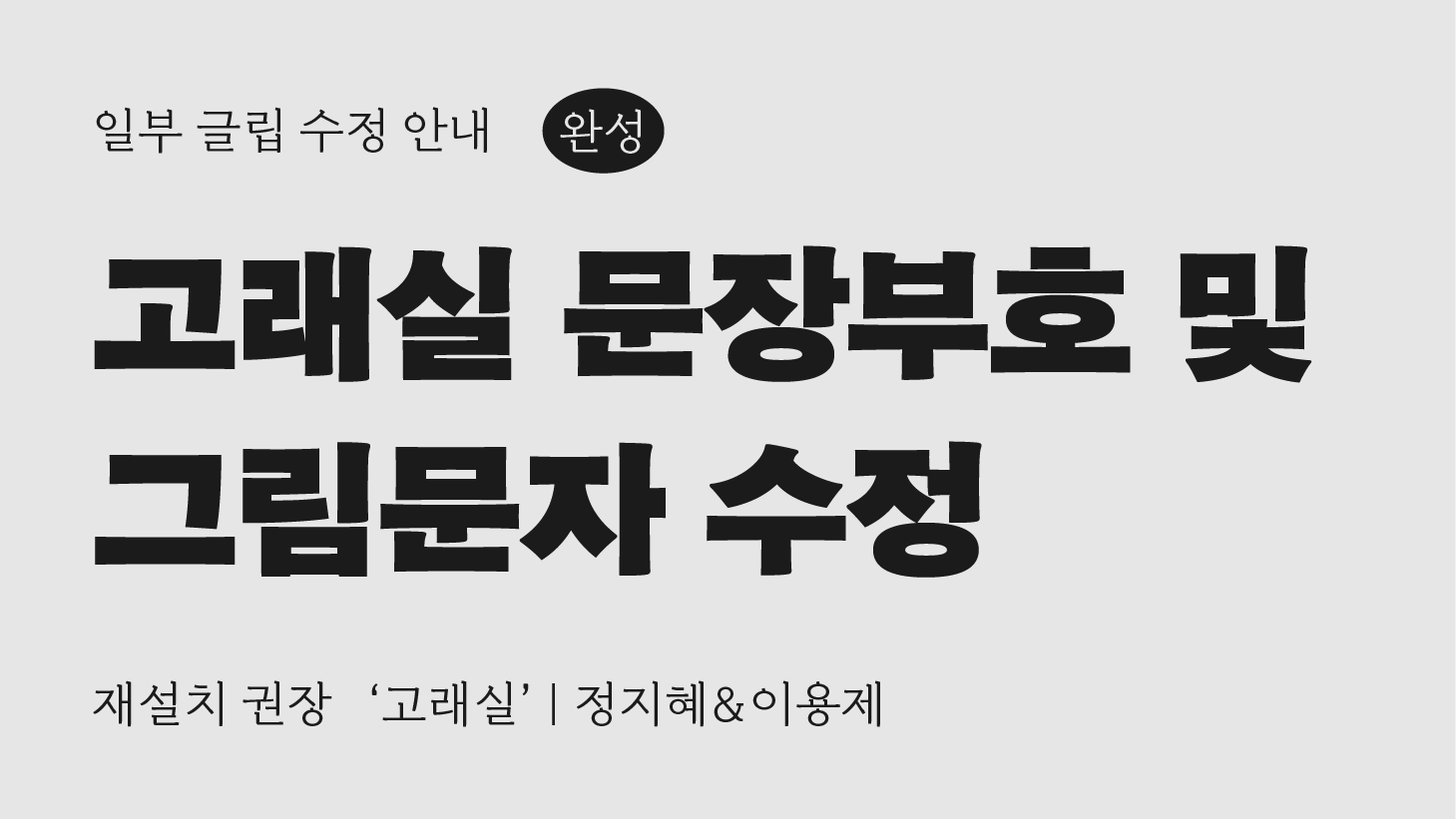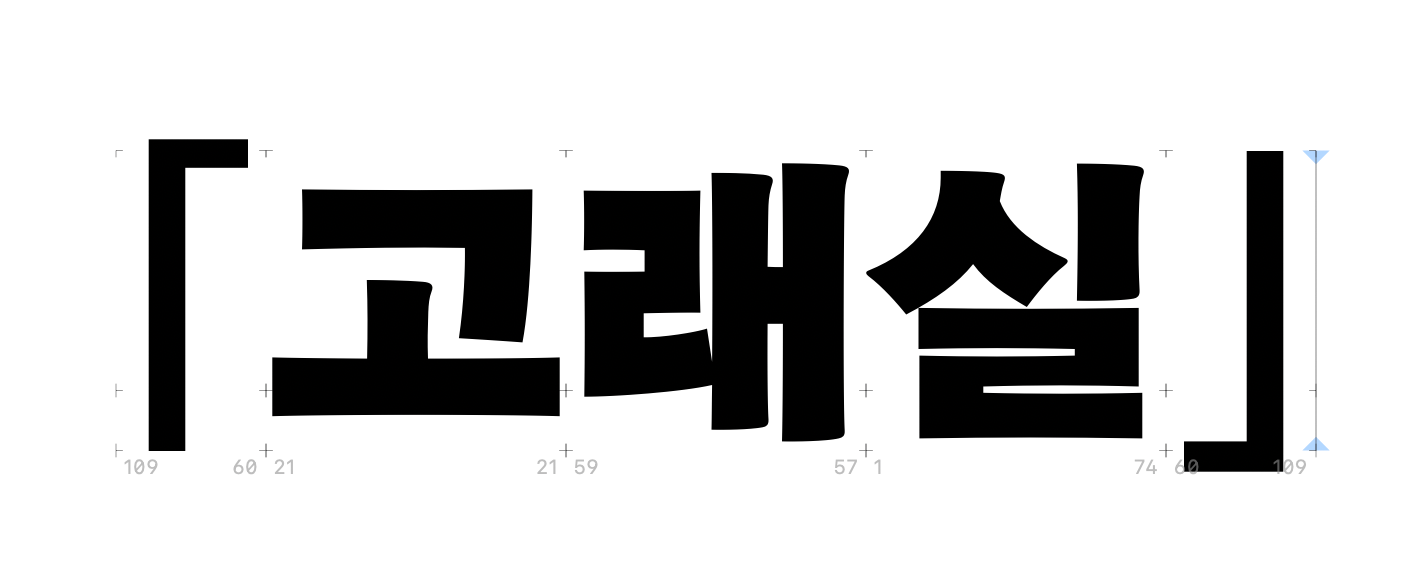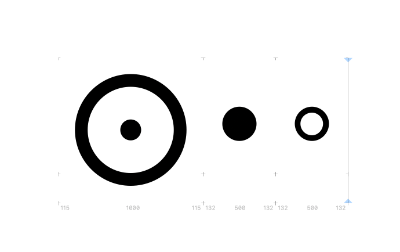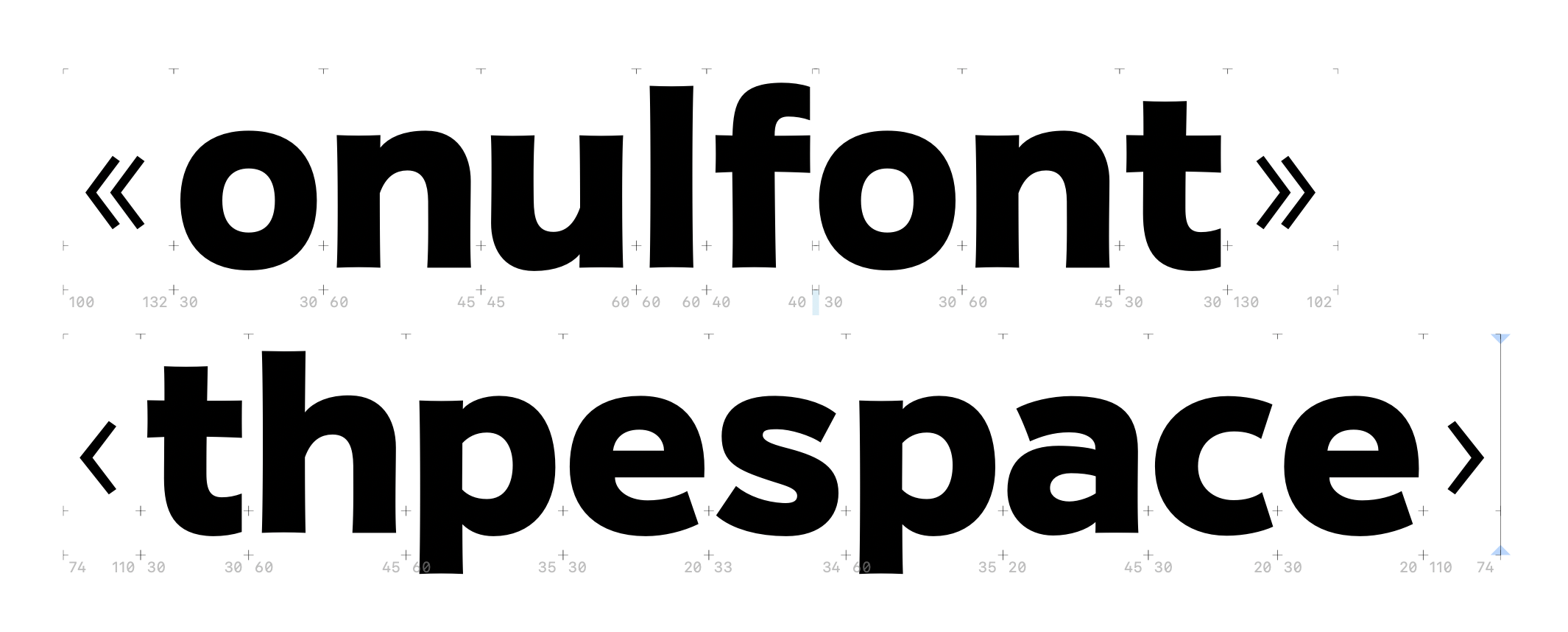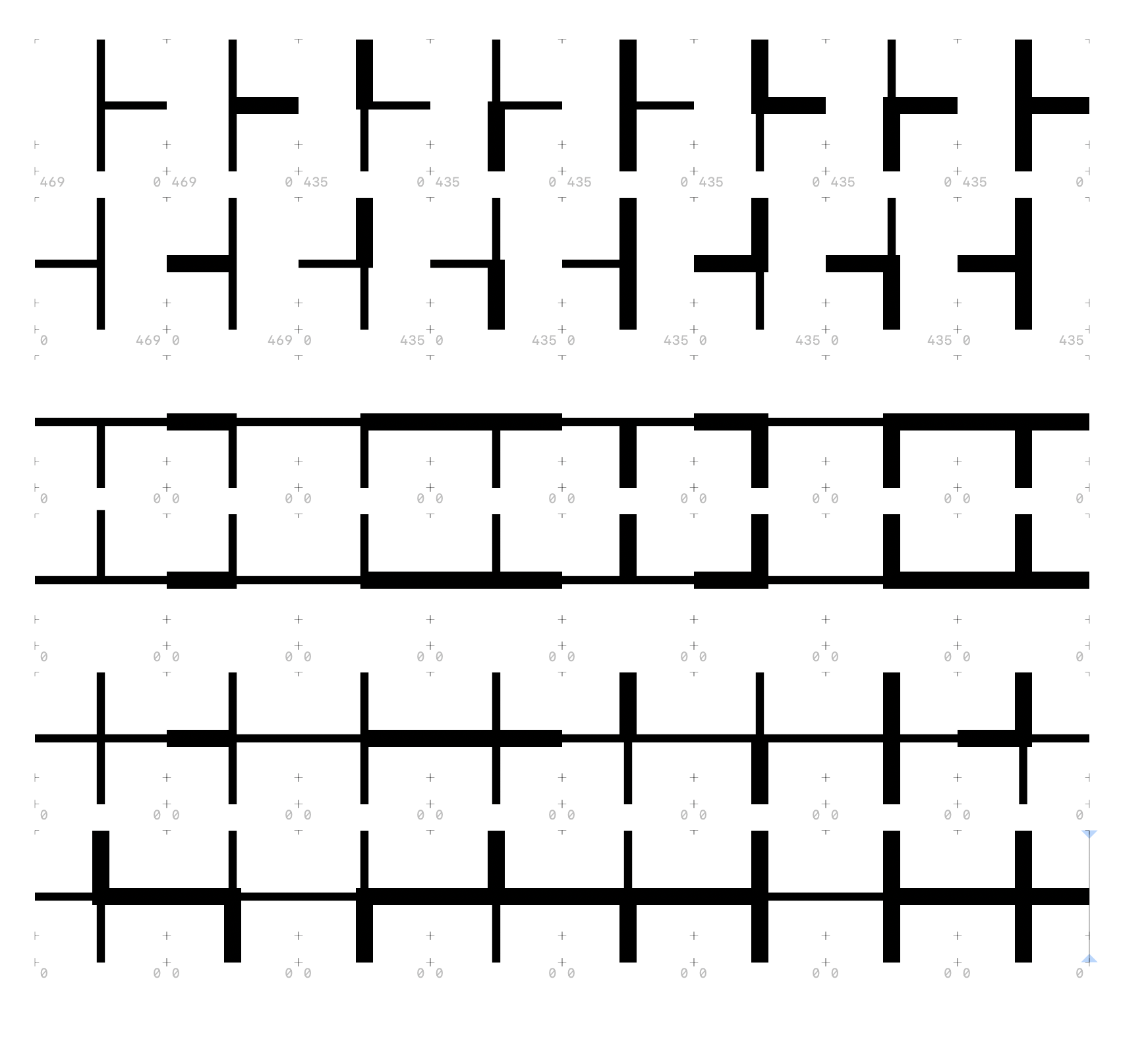
'고래실'의 일부 글립이 잘못 그려진 것을 확인하여, 디자이너님께서 수정해주셨습니다.
수정된 글립은 아래와 같습니다
<수정한 부분>
1. 꺽쇄
2. Operator.circled / WhiteBullet
3. Guillemets(수학기호)
4. 그림문자
크기와 약간의 모양 변화가 있었던 것이라, 기존의 폰트를 사용하셔도 큰 문제는 없을 것으로 보입니다.